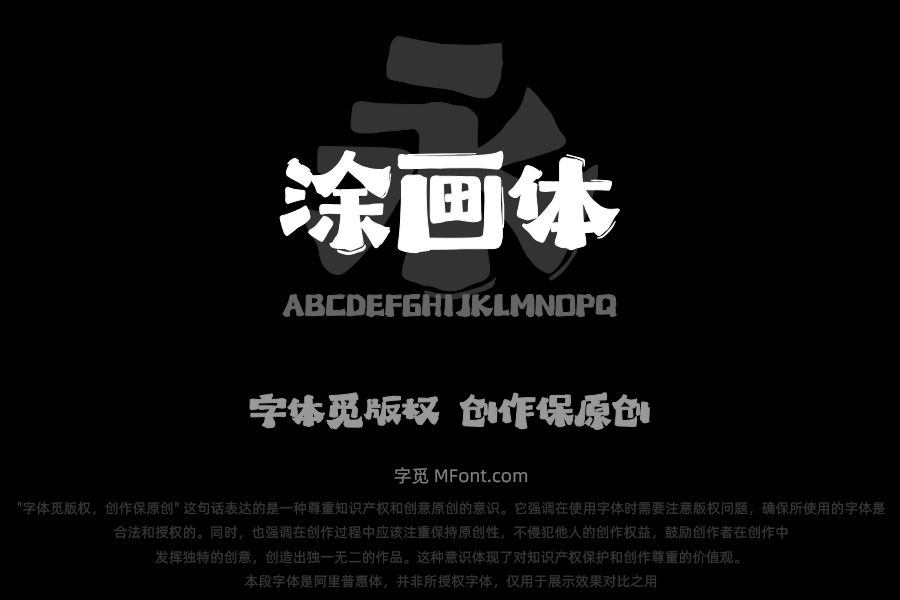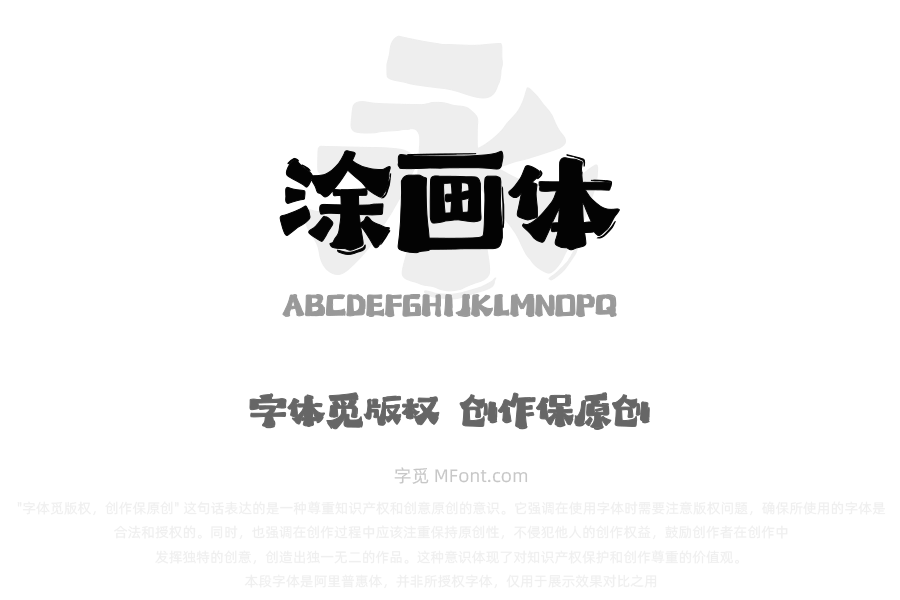
• 上首涂画体
字体全名: 上首涂画体
字体简介: 上首涂画体,简体中文约6763字,字体笔画粗细有致,边缘带有自然的笔触效果,整体风格简洁大方,笔画虽简单但不失个性,字体给人一种悠然自在、缓缓流淌的感觉,粗细变化明显。笔画的粗细变化、边缘的晕染效果等,增添了视觉上的独特魅力,展现出传统与趣味的结合。此款字体多适用于包装、海报、国风、文艺、创意广告等领域。